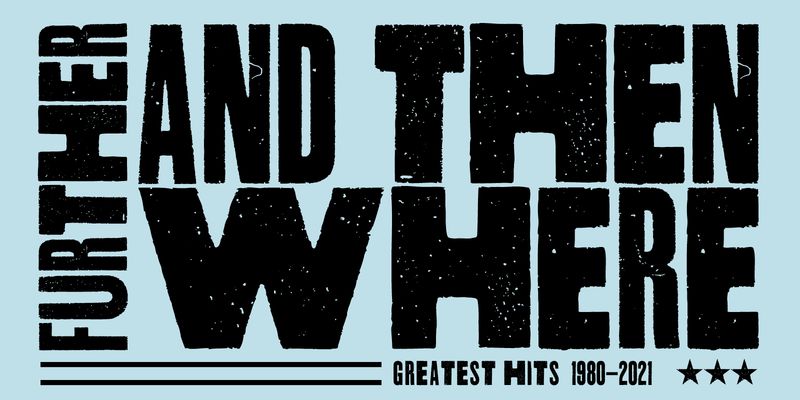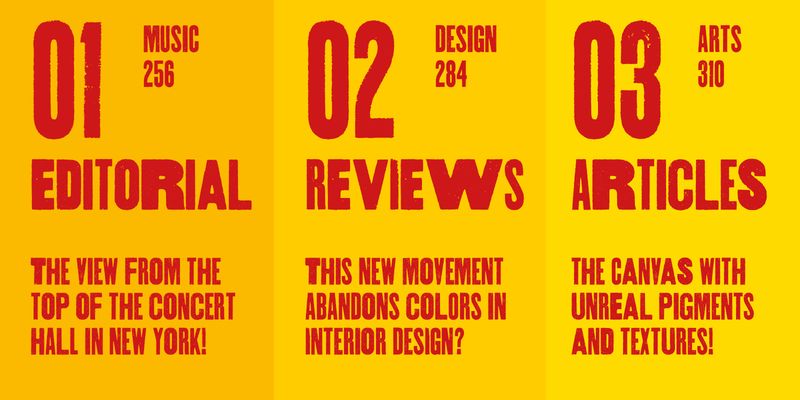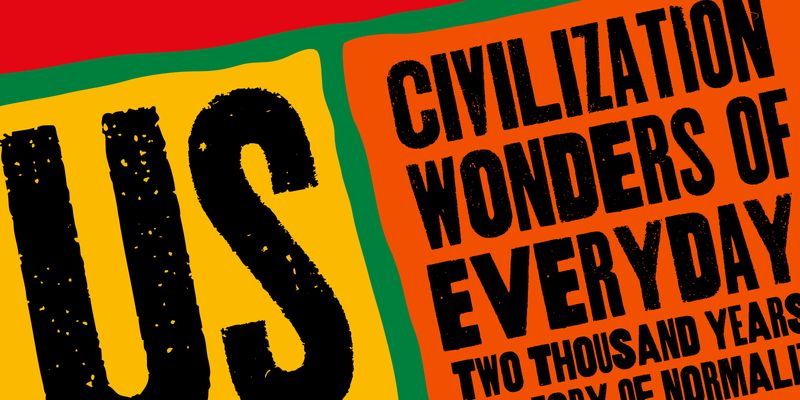
Aerotype은 Stephen Miggas가 만든 소규모 서체 컬렉션을 수용하기 위해 1995년에 설립되었습니다. 오늘날 Aerotype은 Fave, Turbinado 및 Zooja와 같은 손글씨 스크팁트, 원래의 파티나를 그대로 살린 Thunderhouse와 같은 우드 타입 디지털 글꼴과 기타 유용하고 다양한 디스플레이 글꼴로 널리 알려져 있습니다.